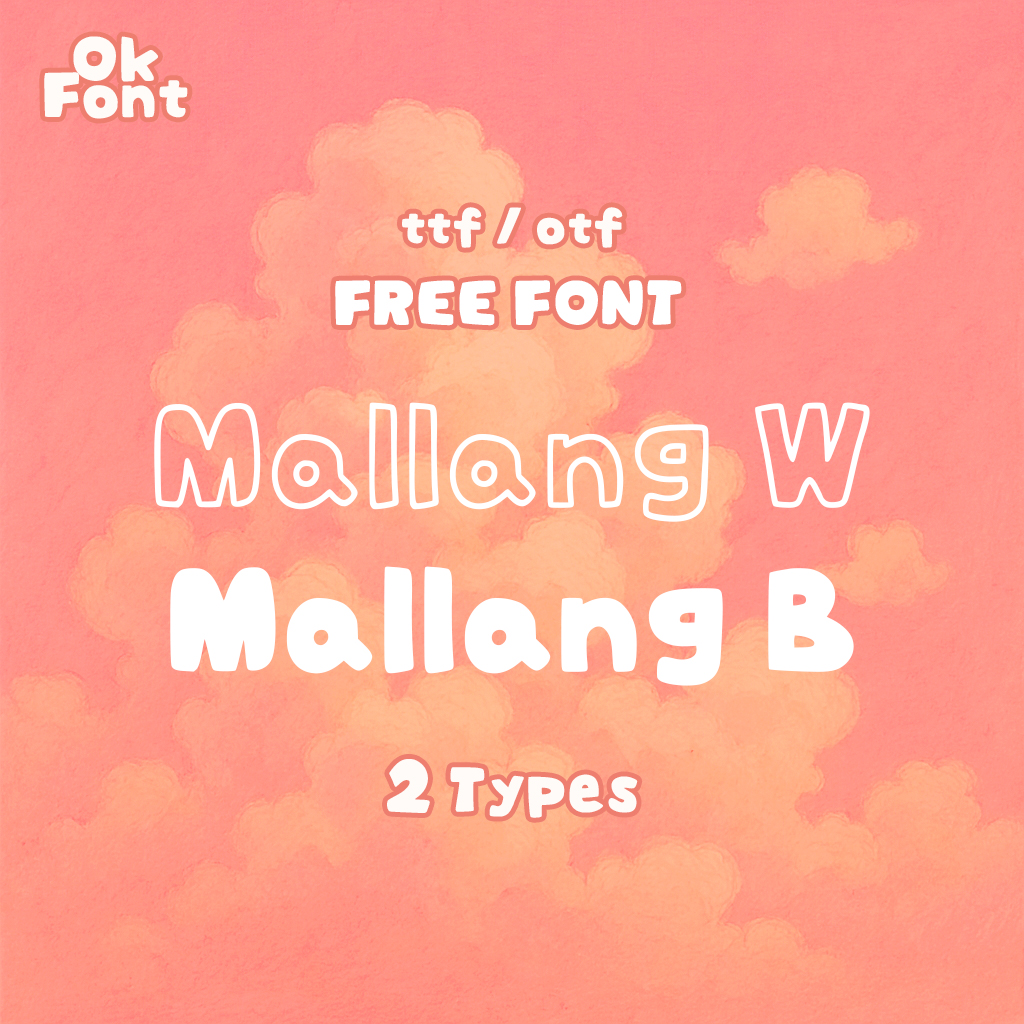
OkMallang — 오케이티콘에서 배포하는 무료 폰트입니다. 말랑한 감성을 담은 친근한 라운드 영문 고딕체
오케이티콘이 2024년 11월에 공개한 영문 전용 서체입니다. 한글은 들어 있지 않으니 한글과 함께 쓰려면 한글 서체를 따로 정해야 합니다.
구성이 특이합니다. 굵기가 아니라 채움 방식으로 두 종이 나뉩니다. Black은 속이 꽉 찬 두꺼운 형태이고 White는 테두리만 남긴 아웃라인입니다. 두 벌을 겹쳐 쓰면 이중 레이어 효과를 낼 수 있습니다.